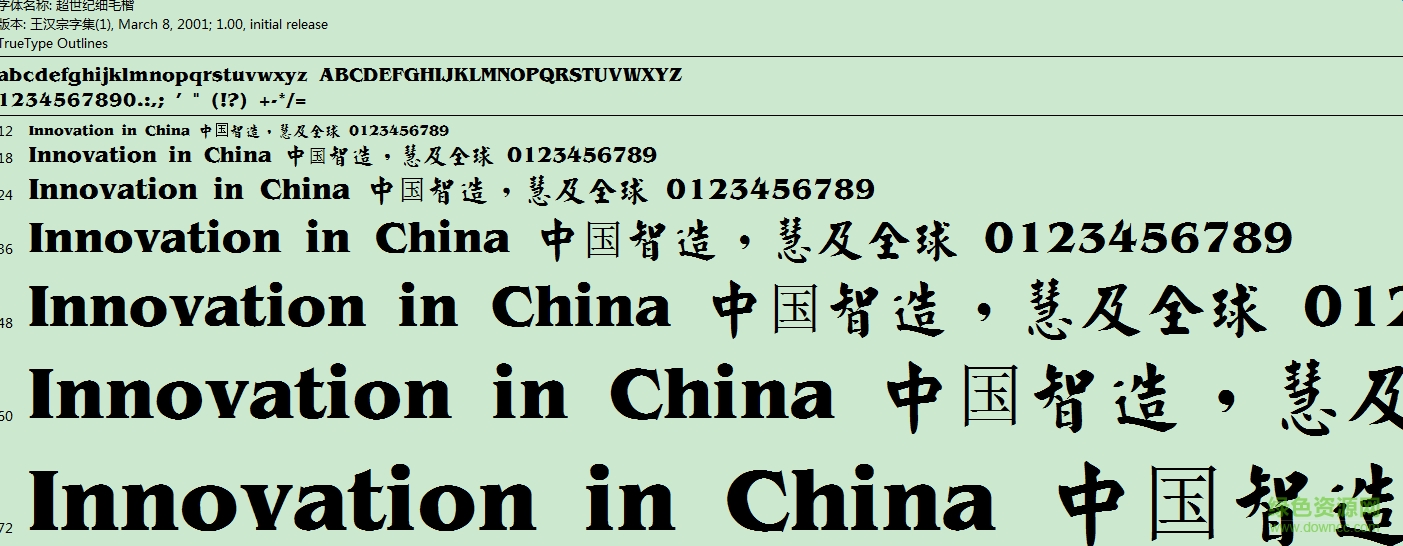
超世紀(jì)細(xì)毛楷字體是一款楷體字體,適用于廣告藝術(shù)設(shè)計(jì)等方面,而且整個(gè)字體使用起來(lái)十分的大氣,整體排版效果也非常的不錯(cuò),有需要的朋友可以來(lái)綠色資源網(wǎng)免費(fèi)下載哦!更多楷體字體等你來(lái)發(fā)現(xiàn)。
一般用于書(shū)籍的前言與圖片的注解部分。在副標(biāo)題和廣告(產(chǎn)品)解說(shuō)(說(shuō)明)部分運(yùn)用的比較多。的傳統(tǒng)韻律比較強(qiáng),所以在傳統(tǒng)類(lèi)的設(shè)計(jì)對(duì)象中運(yùn)用的非常廣,但是是不會(huì)作為主標(biāo)題的文字選擇。